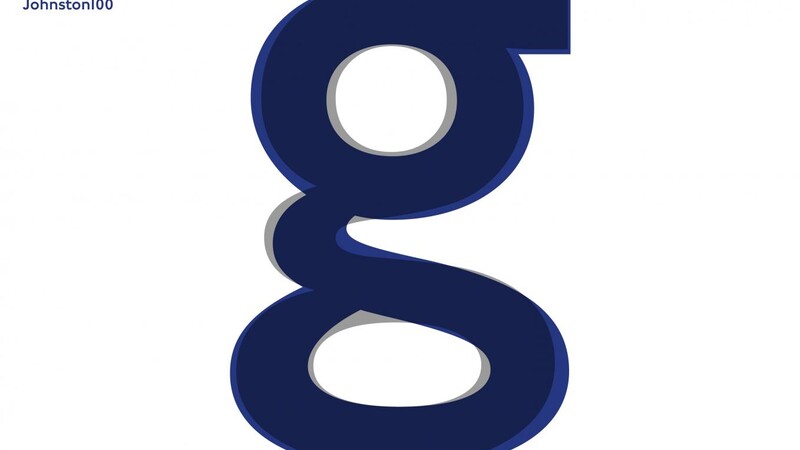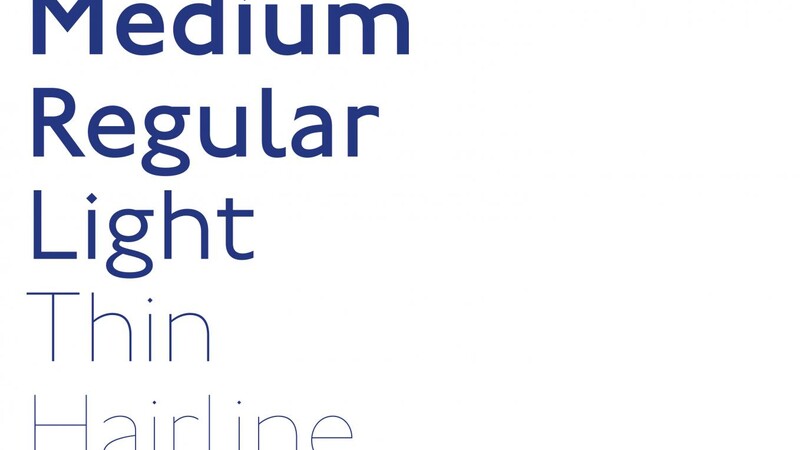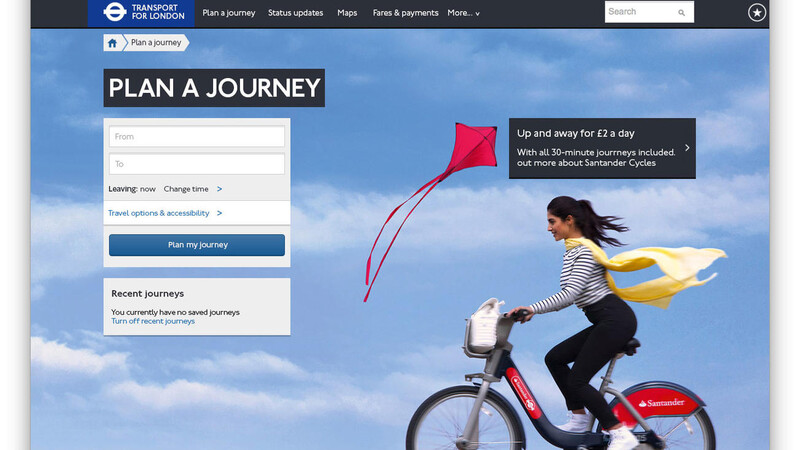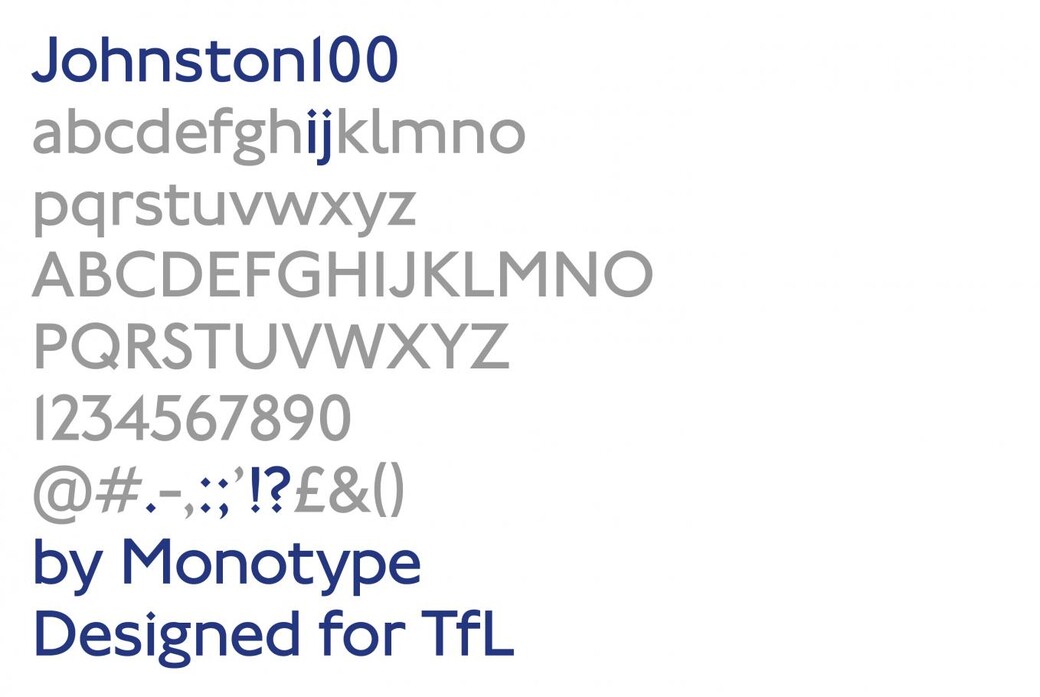
Johnston100: te presentamos la lengua londinense
Te presentamos a Johnston100, la lengua de Londres.
Transport for London encargó a Monotype un proyecto para modernizar el tipo de letra Johnston, que ya tenía 100 años de antigüedad.
El tipo de letra Johnston lleva más de un siglo siendo la expresión tipográfica de Londres y definiendo el carácter visual del sistema de transporte público de la ciudad.
En el año 1913, el artista y calígrafo británico Edward Johnston recibió el encargo de crear una letra con una «simplicidad impactante» que perteneciera en cuerpo y alma al siglo XX, pero que estuviera arraigada en la tradición. El diseñador desarrolló un único grosor para el tipo de letra, cuyas proporciones se basaban en los siete trazos con forma de diamante de un lápiz, que vuelve a estar presente en el punto de la «i» y la «j».
El diseño, estrenado en 1916, ha permanecido prácticamente invariable durante 100 años, aunque a finales de la década de 1970 pasó por una actualización para la tecnología de composición tipográfica contemporánea de la mano de Eiichi Kono, de Banks & Miles. Pese a algunas pequeñas adaptaciones, Johnston ha continuado definiendo el carácter y la identidad visual que tan importantes han sido para Londres, tanto para el turismo como para la población local. Para celebrar su contribución al lenguaje visual de la ciudad, un año se incluyó en la exposición centenaria que tuvo lugar en The Ditchling Museum of Art + Craft del Reino Unido, donde se destacó su posición como un clásico absoluto en el mundo de los tipos.
Nuevas exigencias
Si bien nadie pone en duda que las letras de Johnston han sobrevivido con gran éxito a un siglo de vida, la ampliación del sistema de transporte público de Londres ha planteado nuevas exigencias para el tipo de letra. Dado que la información está presente en cada vez más medios y soportes, desde los mapas de las estaciones hasta las aplicaciones móviles, Transport for London (TfL) se encontró ante una nueva necesidad: expandir y actualizar Johnston sin poner en riesgo las intenciones originales del diseñador.
«Pedimos a Monotype que retrocedieran hasta los principios originales de Johnston para reflexionar sobre el presente de la fuente y descubrir qué puede haberse perdido durante estos 100 años de vida», explicó Jon Hunter, responsable de diseño de TfL.
«No queríamos rediseñarla, pero éramos conscientes de que, por distintos motivos, se habían producido algunos cambios», añadió. «Algunas de las letras minúsculas, por ejemplo, habían perdido su carácter único».
La nueva familia Johnston100 incluye cinco grosores para el diseño, incluidos dos totalmente nuevos: Hairline y Thin. Estas dos incorporaciones demuestran lo difícil que es intentar separar el esqueleto de un tipo de letra del resto de su cuerpo, algo que requiere trabajo tanto de diseño como de investigación. El resultado, especialmente en el caso de Hairline, posee un sabor contemporáneo sin debilitar sus características identificativas.
La idiosincrasia entra en escena
Para regresar a las raíces del tipo de letra y conservar la identidad, Monotype designó a la directora de tipos Nadine Chahine y al diseñador de tipos sénior Malou Verlomme para que examinaran a fondo los dibujos de los archivos. Juntos, identificaron los elementos que se habían perdido a lo largo de años de evolución, como la cola diagonal característica de la letra «g» minúscula y la mayor anchura de la letra «U» mayúscula.
«Las últimas versiones habían empezado a volverse algo más mecánicas y un poco uniformes», comentó Chahine. «El tipo de letra poseía algunas idiosincrasias que, pese a que nos parecían poco convencionales, eran buenas. Si conseguimos traerlas de vuelta, podríamos recuperar parte del espíritu original».
El equipo de diseño también examinó los carteles antiguos de TfL, donde solía ponerse énfasis en la alegría que podía transmitir el metro, algo que ha perdido prominencia en las comunicaciones actuales. Chahine y Verlomme esperan que el hecho de recuperar un diseño algo más ancho permita volver a incorporar la sensación de espacio tanto al tipo como a la experiencia de usar el metro.
«No se trata de la mecánica ni de la perfección», añadió Chahine. «Se trata de aceptar los detalles pequeños y poco convencionales».
«Nos gusta pensar en nuestra imagen de marca y nuestros carteles como un miembro invisible de la plantilla». ”
Un compañero inseparable
TfL empezó a utilizar Johnston100 en julio de 2016. Inicialmente, el tipo de letra se utilizó en los materiales impresos, como los pósteres y mapas del metro, para luego dar el salto a los trenes y los carteles de las estaciones de TfL, incluida la línea londinense Elizabeth Line (Crossrail), que se inauguró en 2018.
«Nos gusta pensar en nuestra imagen de marca y nuestros carteles como un miembro invisible de la plantilla», declaró Hunter. «Es como tener a alguien acompañándote durante todo el proceso», comentó Chahine. «El tipo de letra y el lenguaje del diseño se diferencian de cualquier otro».